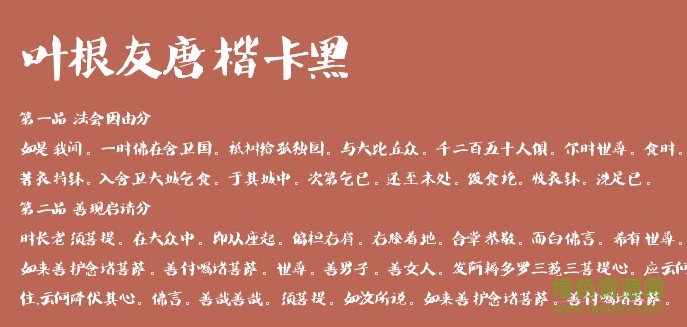
葉根友唐楷卡黑是一款由大唐楷體書法風(fēng)格的葉根友字體,為你的文學(xué)排版、詩詞編輯更添古風(fēng)魅力,流暢的筆法和柔軟的線條為大家所喜愛,綠色資源網(wǎng)歡迎大家下載!
葉根友唐楷卡黑是由葉根友開發(fā)設(shè)計(jì)的一套獨(dú)特的楷書字體,風(fēng)格區(qū)別于傳統(tǒng)書法楷書的中規(guī)中舉,在筆畫運(yùn)筆以及起筆等方面均有創(chuàng)新性的突破,在行筆中起伏變化。